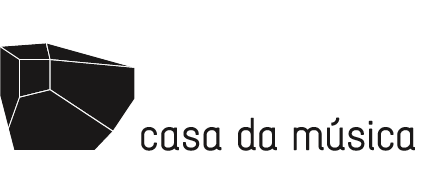
Schrift von casa da música
Erinnert mich an "Simple" von lineto … :-?
Fraglich, ob das überhaupt eine unveränderte Satzschrift ist oder ob nicht eher eine Satzschrift als Grundlage für ein gestaltetes Logo dient.
Mit Firefox auf die Seite gehen, einen Text mit der Schrift markieren, ich habe "Orquestra Sinfónica do Porto Casa da Música" ausgewählt, dann Maus rechtsklicken und das JavaScript Whatfont zeigt Simple Bold an.
Mit Element untersuchen (Q) im Pop-Up-Menu auswählen erhält man ...
Verwendet: "SimpleBold"
[Fontforge -> Menu Element -> Schrifteigenschaften und dann -> PS-Names, Feld Urheber:
Es ist also die Simple Bold von Lineto ...
Nö, die Simple sieht doch zum Großteil anders aus … siehe erster post ;-)
sagmeister hat über die entstehungsgeschichte mal einen vortrag auf der typo gehalten, war sehr informativ und der ansatz gefällt mir ganz gut. eine der wenigen arbeiten von sagmeister mit denen ich was anfangen kann.